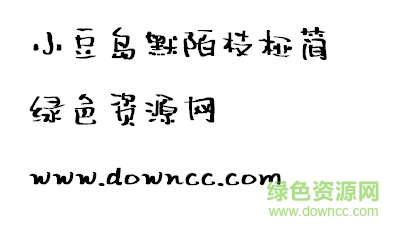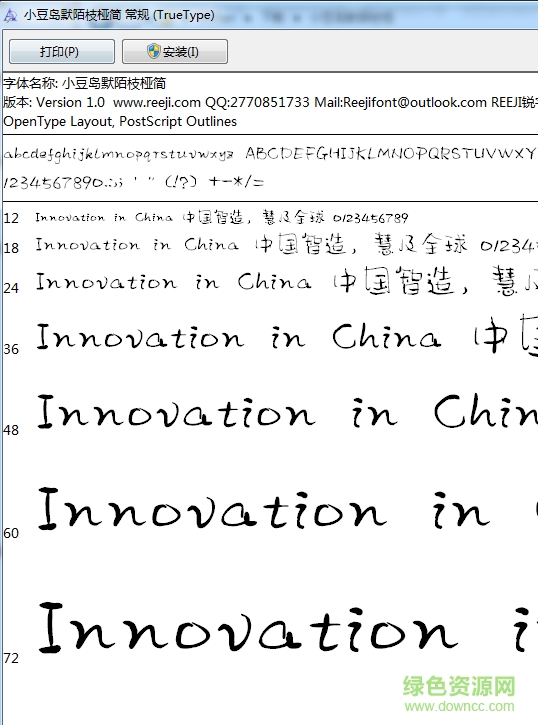
小豆島默陌枝椏字體是一款時(shí)尚風(fēng)格手寫字體軟件,該字體筆畫隨心所欲,整體給人放浪不羈的感覺,韻味十足,喜歡就到綠色資源網(wǎng)下載使用吧!
小豆島默陌枝椏簡(jiǎn)字體家族系列主要提供常規(guī)等字體風(fēng)格樣式,字庫完整,可以廣泛應(yīng)用于名片設(shè)計(jì)、新聞媒體、宣傳海報(bào)、ppt、影視制作以及內(nèi)容用字等領(lǐng)域。